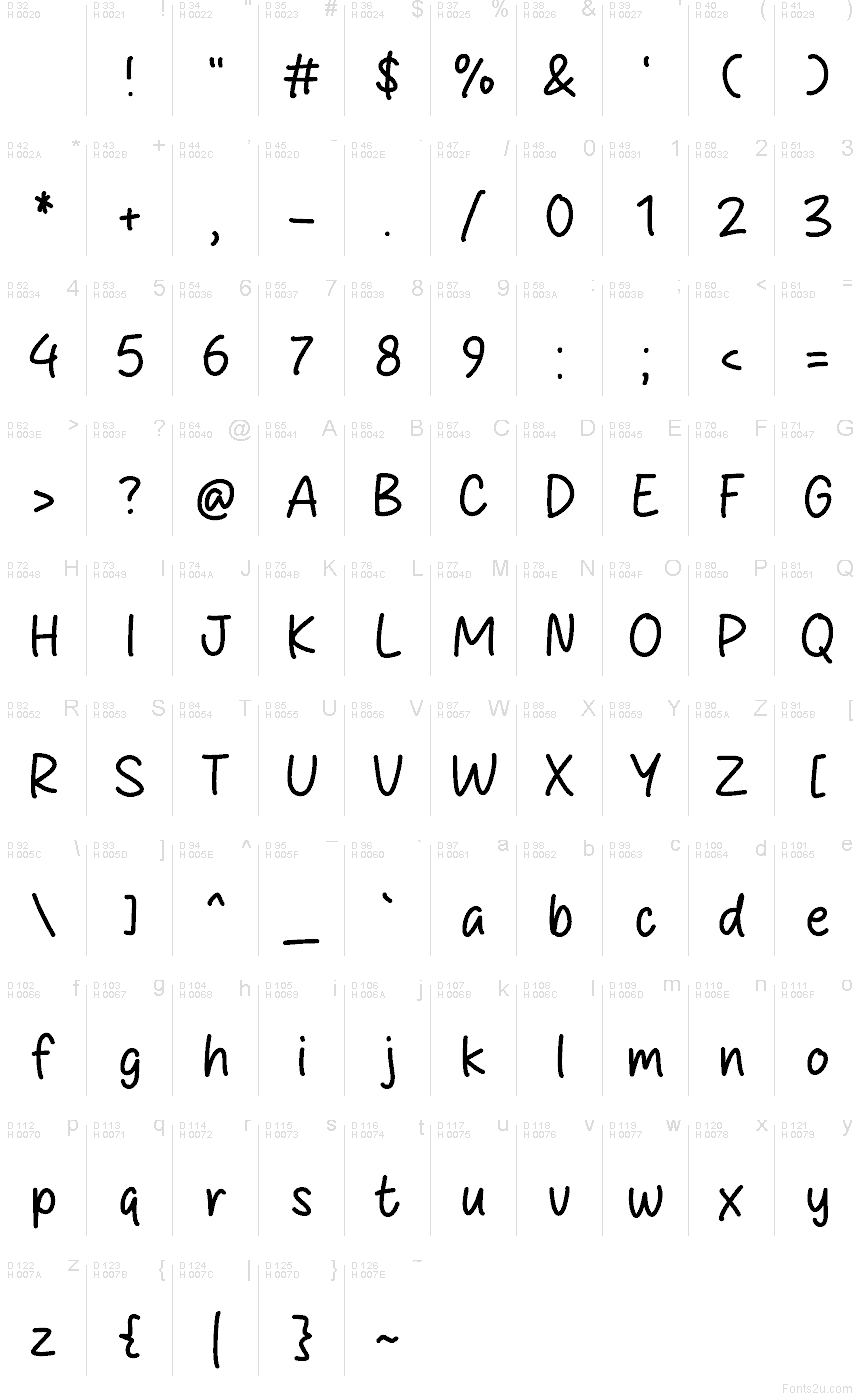
Study Night
Study Night od MJType je bezplatné rukopisné písmo, které má lehký rytmus jako psaní fixem. Zaoblené znaky a lehce proměnlivá linka udržují písmo neformální a osobní – působí spíše jako úhledná poznámka v bloku než jako vybroušený krasopis.
Je to přirozená volba pro studijní plánovače, obaly na poznámky, kartičky, nadpisy deníků nebo hlavičky pracovních listů, kde působí přátelský rukopisný dotek mnohem přesvědčivěji než formální styly. Skvěle ukotví také školní grafiku na sociálních sítích nebo tištěné štítky, zejména když hledáte písmo, které působí uvolněně, přímočaře a důvěrně.